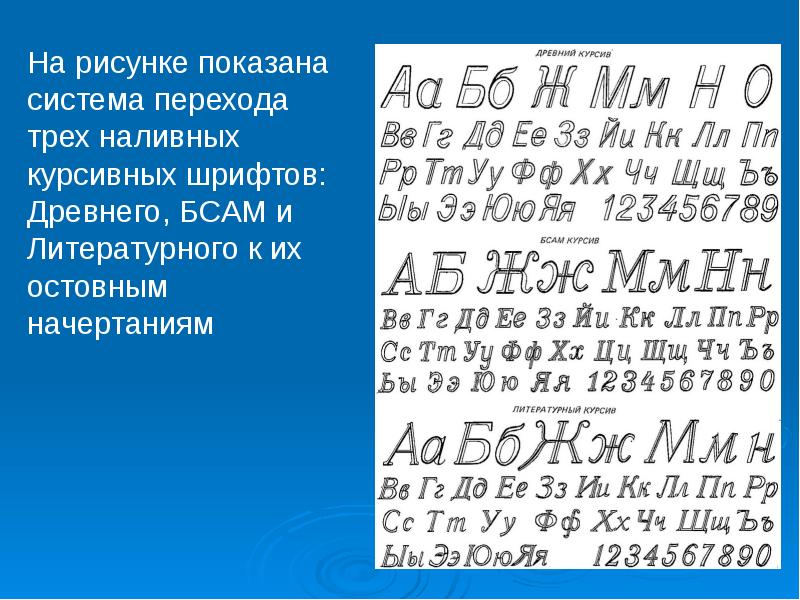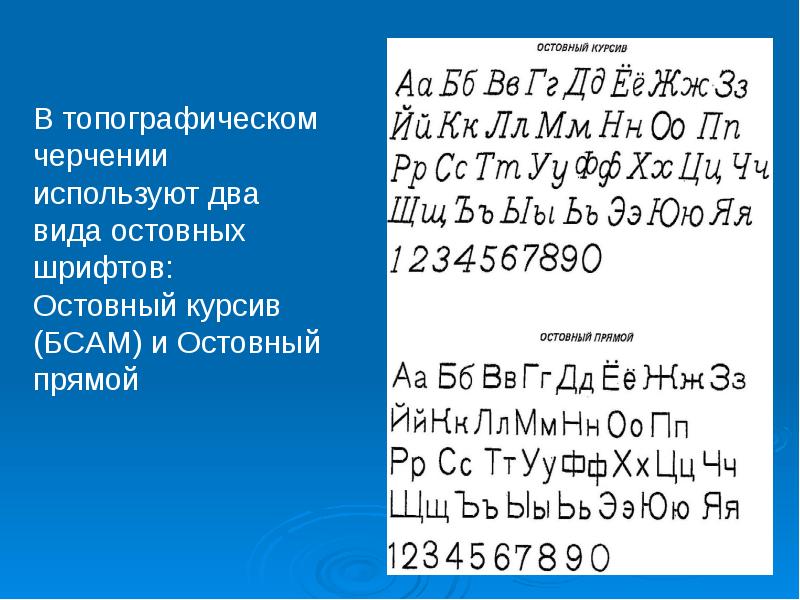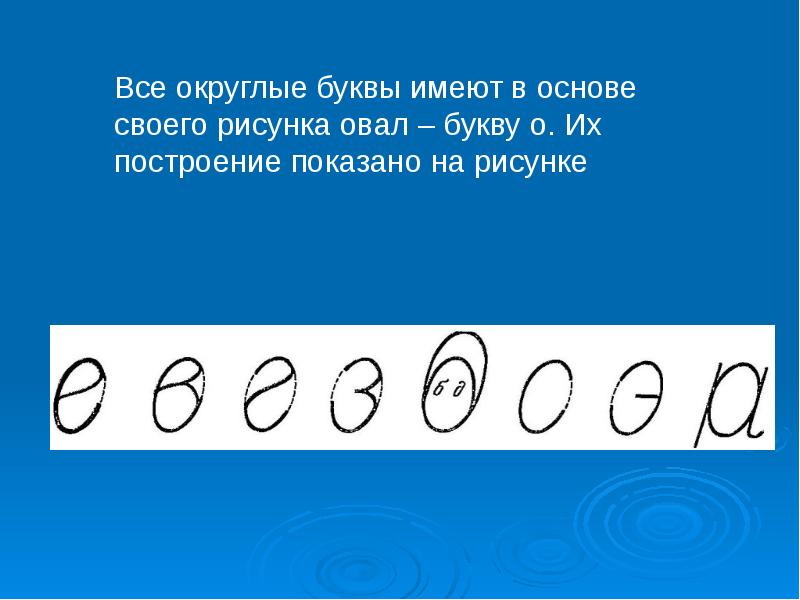
ТОПОГРАФИЧЕСКОЕ ЧЕРЧЕНИЕ
ШРИФТЫ И НАДПИСИ НА КАРТАХ
6.1 ЗНАЧЕНИЕ НАДПИСЕЙ НА КАРТАХ На картах различного содержания, назначения и масштабов изображение природных и социально-экономических объектов и явлений условными знаками дополняется надписями
6.2 ОСТОВНЫЕ ШРИФТЫ И МЕТОДИКА ВЫЧЕРЧИВАНИЯ БУКВ И СЛОВ Правильное вычерчивание надписей на съемочных и составительских оригиналах карт основывается на знании особенностей различных шрифтов и соблюдении правил их построения.
6.3 ПРАВИЛА РАЗМЕЩЕНИЯ ПОДПИСЕЙ НАЗВАНИЙ ОБЪЕКТОВ НА КАРТАХ Населенные пункты. Название населенного пункта располагают по строке, параллельно северной (южной) рамке карты или вдоль параллелей, преимущественно справа от изображения пункта